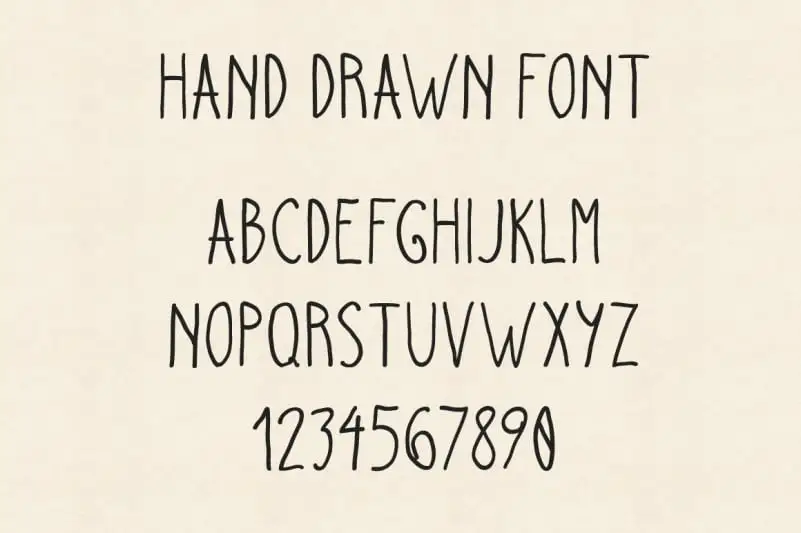
Hand Drawn Script Font – Download Grátis
A ‘Hand Drawn Script Font’ é uma tipografia moderna que se destaca por sua elegância e naturalidade. Inspirada na arte do traçado a mão, esta fonte atende perfeitamente aos diversos usos digitais atualmente populares, como posters, logomarcas, embalagens, convites de festa e títulos em websites. Suas linhas fluidas e nuances distintas garantem um toque sofisticado que combina perfeitamente com o estilo moderno da tipografia moderna. Afinal, a ‘Hand Drawn Script Font’ é uma escolha ideal para quem busca um visual cuidadosamente cuidado e autêntico em qualquer projeto digital.